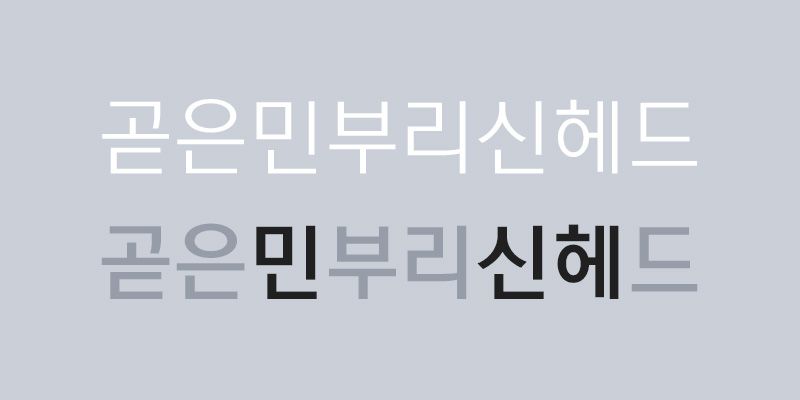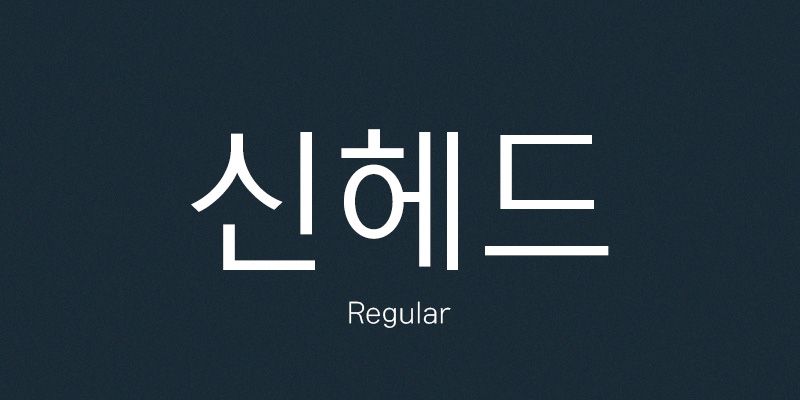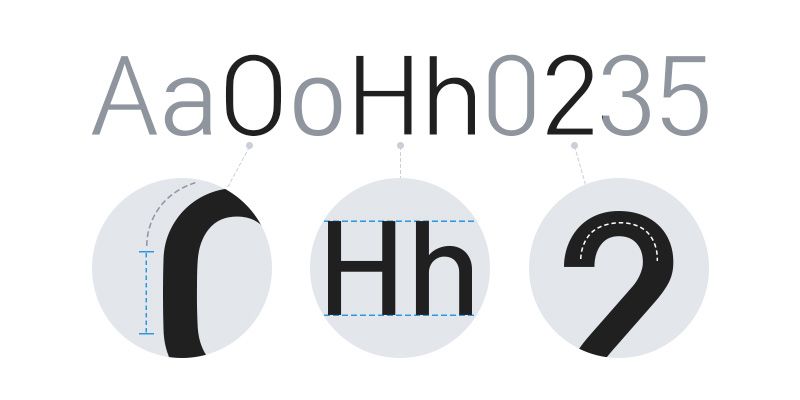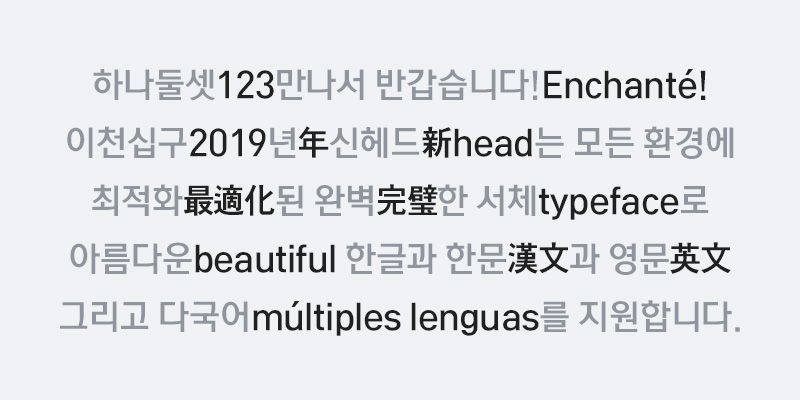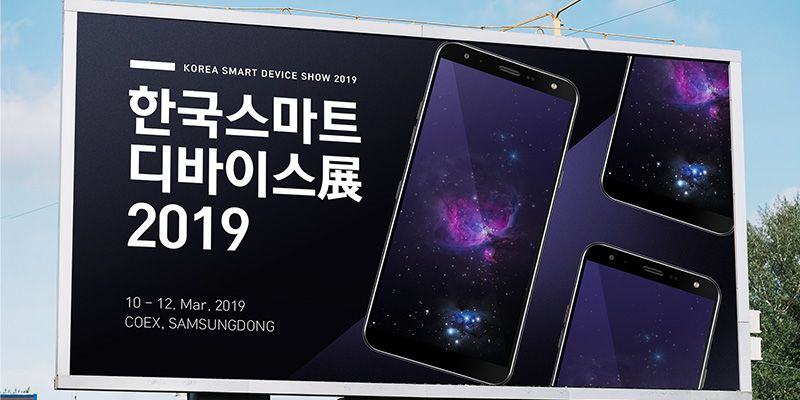
Con una distribuzione delle linee e dello spazio altamente leggibile e ottimale che si ottiene attraverso spazi più ampi, questo font gotico per i titoli è ottimizzato per vari ambienti.